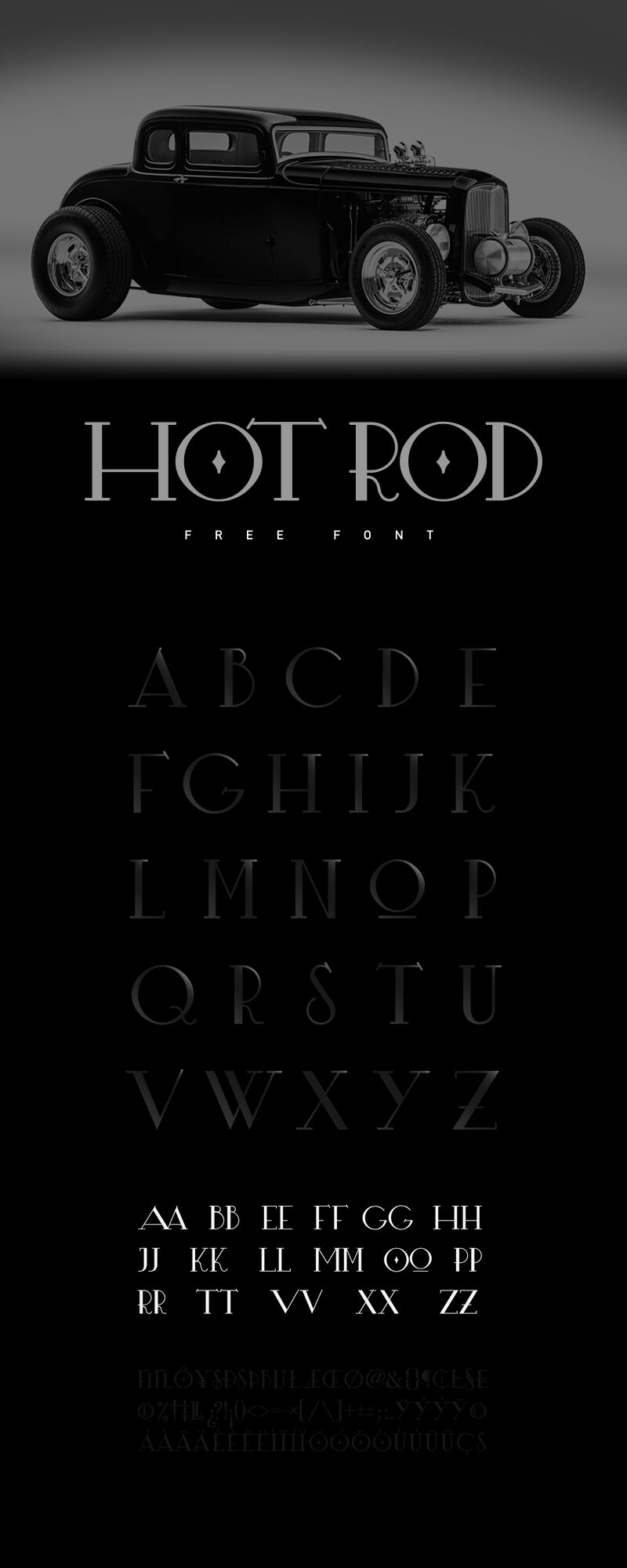
Tano Veron 设计的 Hot Rod 是一款复古衬线字体,其质感宛如铬合金般的字母化作了鲜明的墨迹。其修长的字体结构、纤细的水平笔画与圆润的内部空间,令人联想到经典的复古改装车店招牌与古董车标,同时兼具清爽的编辑设计感。紧凑而有意的字距创造出优雅且连贯的节奏,在屏幕显示上锐利醒目,在印刷中则饱满浓郁。
Hot Rod 是一款免费字体,在海报、Logo、活动标题、酒类或香水标签、复古包装以及极具冲击力的杂志排版中表现出色。其雕塑般的字体造型非常适合大字号展示,建议在标题和品牌字标中让其充分展现,并搭配简洁的无衬线字体作为正文,以保持版面的平衡与易读性。